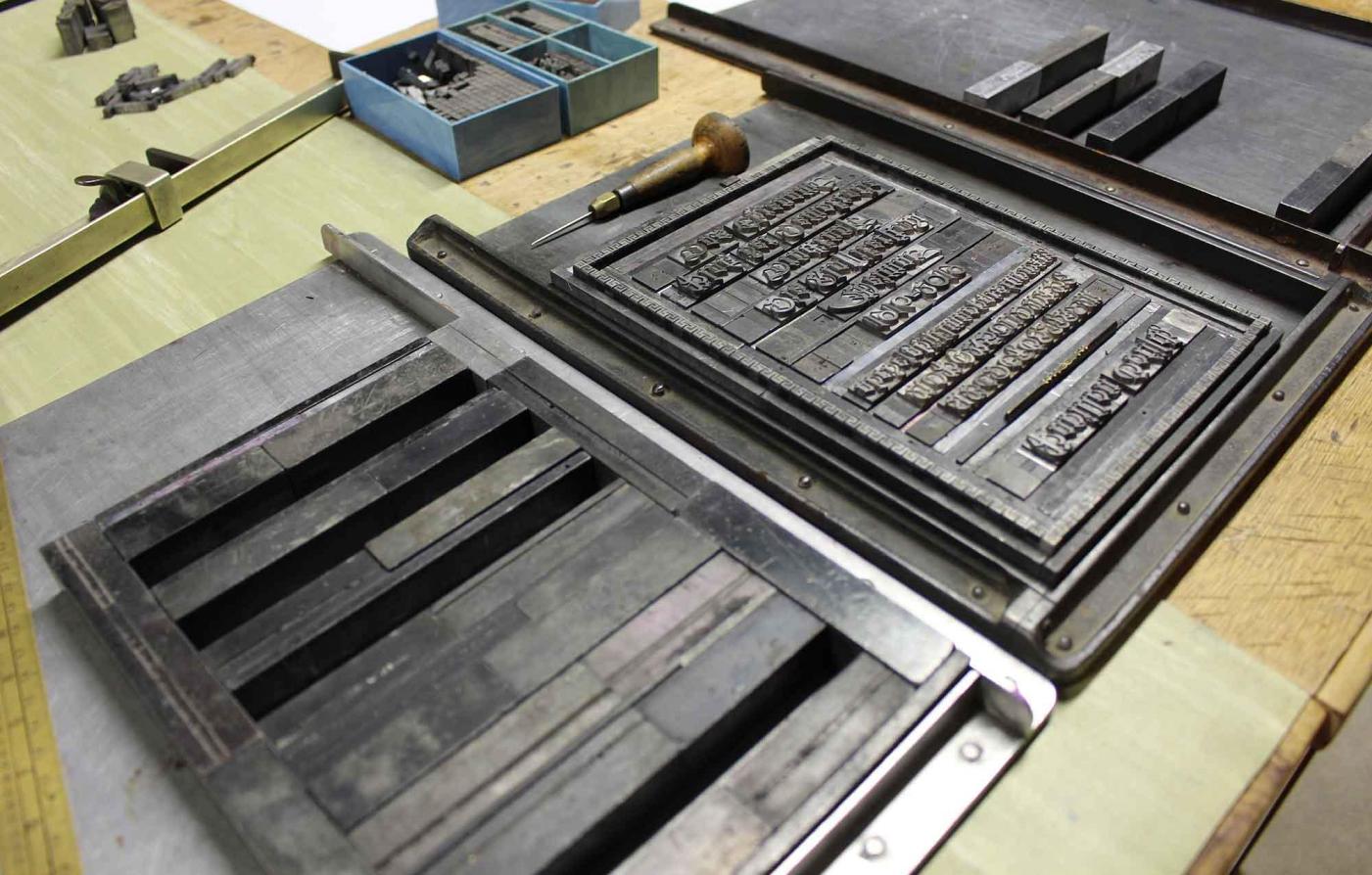
Fragen um FDI Mainzer Initialen
Da habe ich jetzt doch zwei Fragenkomplexe, die sich an der Schrift aufhängen:
1. Bedeutet die Desktop-Variante, dass dort die Farben nicht individuell festgelegt werden können? Ich habe Deinen Artikel den Möglichkeiten der neuen Fonterweiterungen gelesen, daher kam mir die Frage, ob das eine bewusste Entscheidung von Dir als Künstler ist, die Farben (ich liebe übrigens den Farbton Safran, ist das eine gebräuchlicher Farbenbezeichnung der damaligen Zeit gewesen für Orange?) so und nicht anders festzulegen?
2. In dem Artikel erwähnst Du, dass damals zweifarbige Initialen im Bleisatz verfügbar waren. Wie wurde das realisiert? Hat man die betreffenden Seiten zweimal drucken müssen? Oder gab es eine Technik, das in einem Rutsch zu machen?
Ja, genau. Man ruft fertige SVG-Grafiken als Glyphen ab. Da können auch Bitmap-Bilder, Verläufe und so weiter drin sein. Der Schriftnutzer kann das also nicht direkt umformatieren.
Zwei unabhängige Druckdurchgänge und also doppelter Aufwand. Deshalb war Mehrfarbigkeit früher eher selten. Im Hinterzimmer hatte ich ja mal ein Beispiel gezeigt und beschrieben.